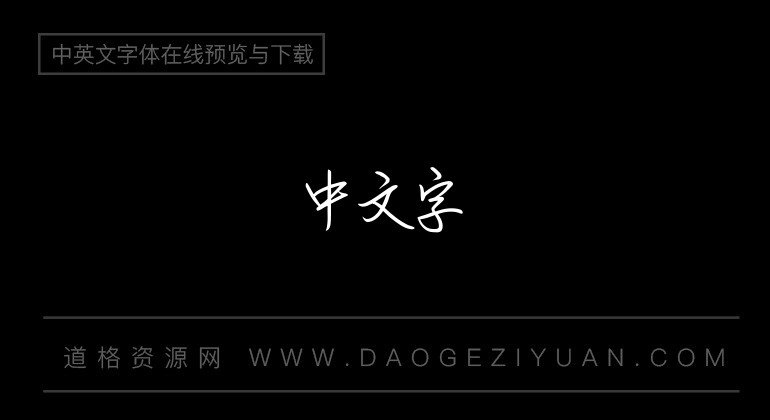
蒙纳简喜宴体
蒙纳简喜宴体字体是一款由蒙特利尔设计师Karine Proulx设计的欧洲风格字体,它体现了简洁、优雅、精致的设计风格,是一款经典的欧洲风格字体。该字体具有良好的可读性,其轮廓线条细腻,字体层次分明,字母形状精确,为文本带来了清晰的视觉效果。它主要用于各种设计领域,如印刷品、海报、标志、包装、网站设计等,可以满足不同场景的设计需求。
蒙纳简喜宴体是一款非常不错的手写艺术字体,具有很好的视觉感,适合于文化类的宣传设计、商业类品牌的广告和产品包装设计以及个性化文字排版等较多场景。